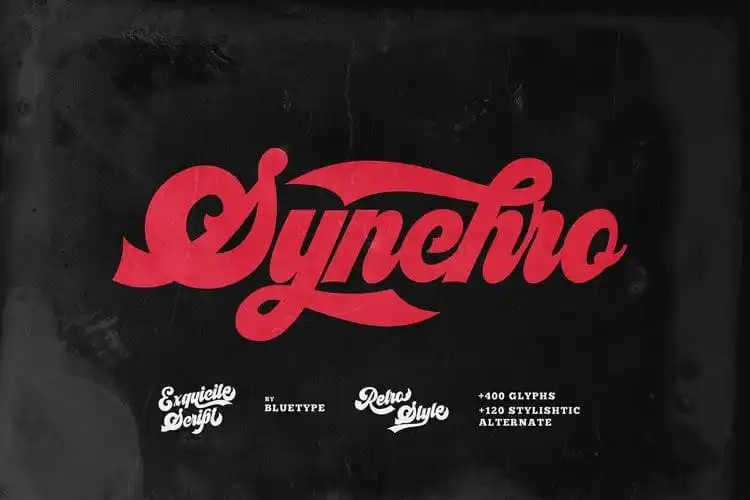
Synchro Script Font – Download Grátis
A Synchro Script Font é uma fonte que captura a essência dos tempos modernos através de vibrações retro e groove do mundo musical, bem como elementos descolados do universo esportivo americano, especialmente da cultura esportiva da bola de basebol e basquete. Com sua inspiração na design retro dos anos 70 e 80, a fonte é perfeitamente projetada para designers que buscam trazer uma dose única de elegância à suas criações. Fundada pelo designer tipo Bluetype, esta fonte sobressai com seus alternativos estilísticos e acabamentos elegantes, tornando-a um recurso indispensável para logotipos, camisetas vintage, selinhos retro, embalagens, marca de produto ou qualquer outro design que exija uma pitada de sofisticação. A Synchro Script Font é a escolha ideal para estilos futuristas, mas também oferece um encaixe perfeito nos elementos retrô e descolados do mundo moderno.